日本語のロゴ・メイキング 漢字・ひらがな・カタカナのロゴづくり
甲谷一氏、リンクアップ、グラフィック社編集部の編集による実際に採用されたロゴのメイキング25事例を紹介した「日本語のロゴ・メイキング 漢字・ひらがな・カタカナのロゴづくり」がグラフィック社から2016年10月7日に発売された。
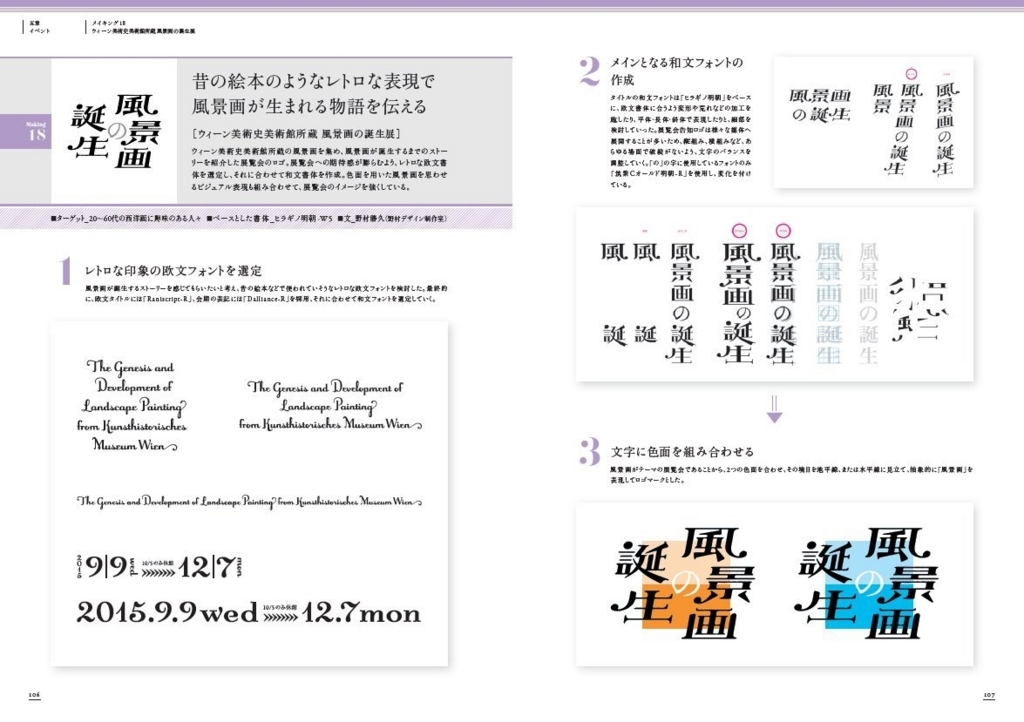
日本語(漢字・ひらがな・カタカナ)で作られたロゴに特化した資料集です。実際に採用されたロゴがどのようなコンセプトで作られ、造形的なブラッシュアップをされていったか、そのメイキングを25事例紹介。シンプルで信頼感を与えるような企業ロゴから、遊び心のあるイベントなどのタイトルロゴまで、幅広く日本語ロゴの持つ楽しさを伝える1冊です。また、メイキング以外にも、様々なジャンルのロゴおよび展開例を多数収録。